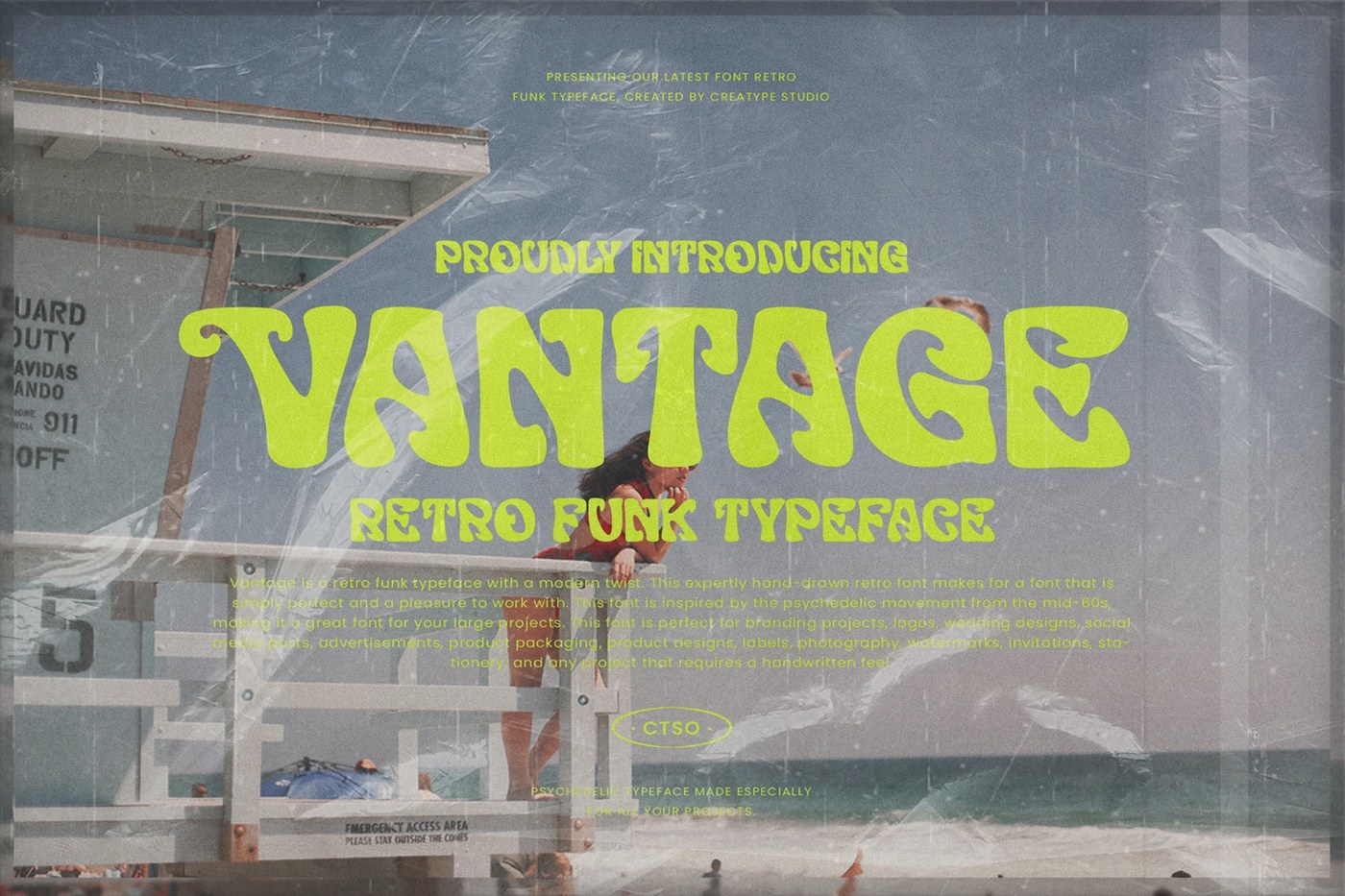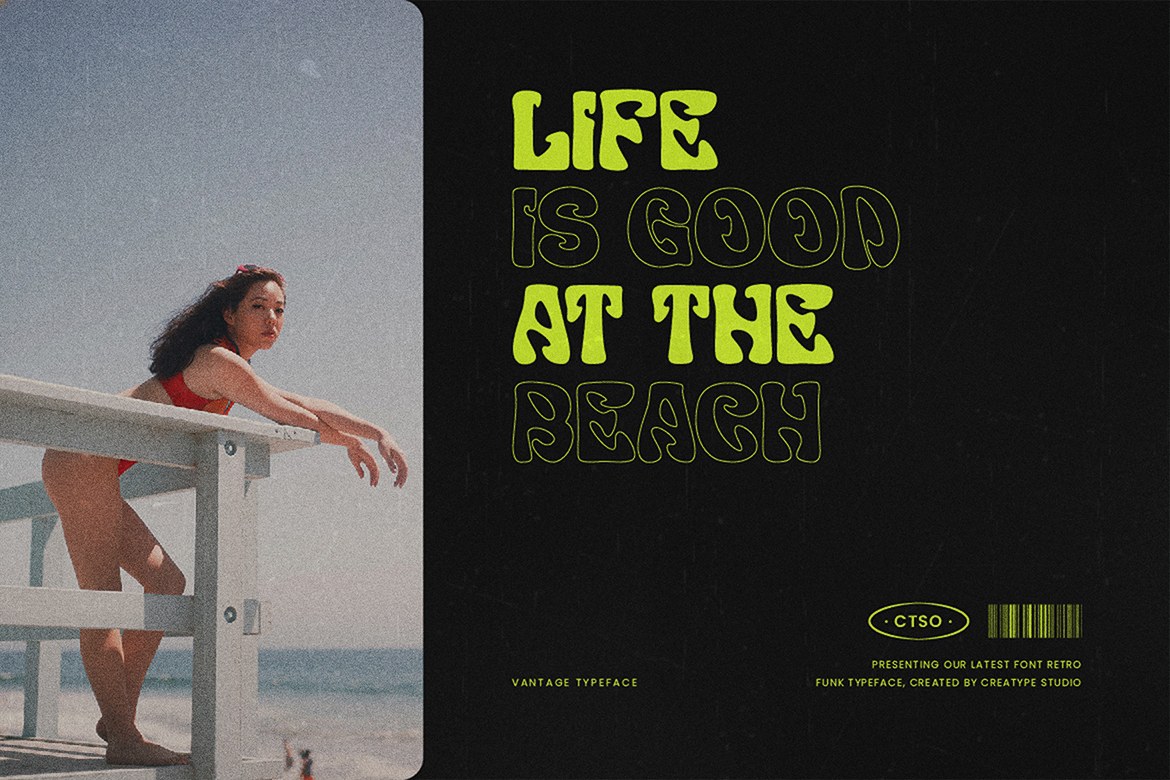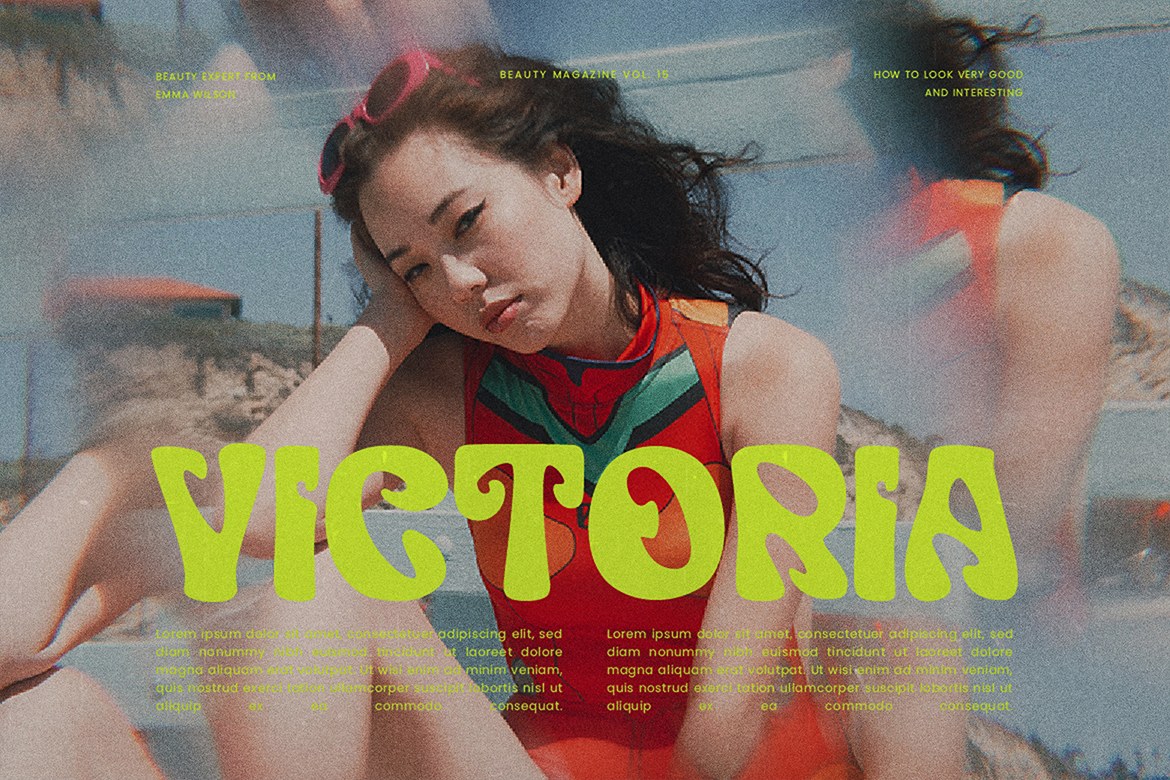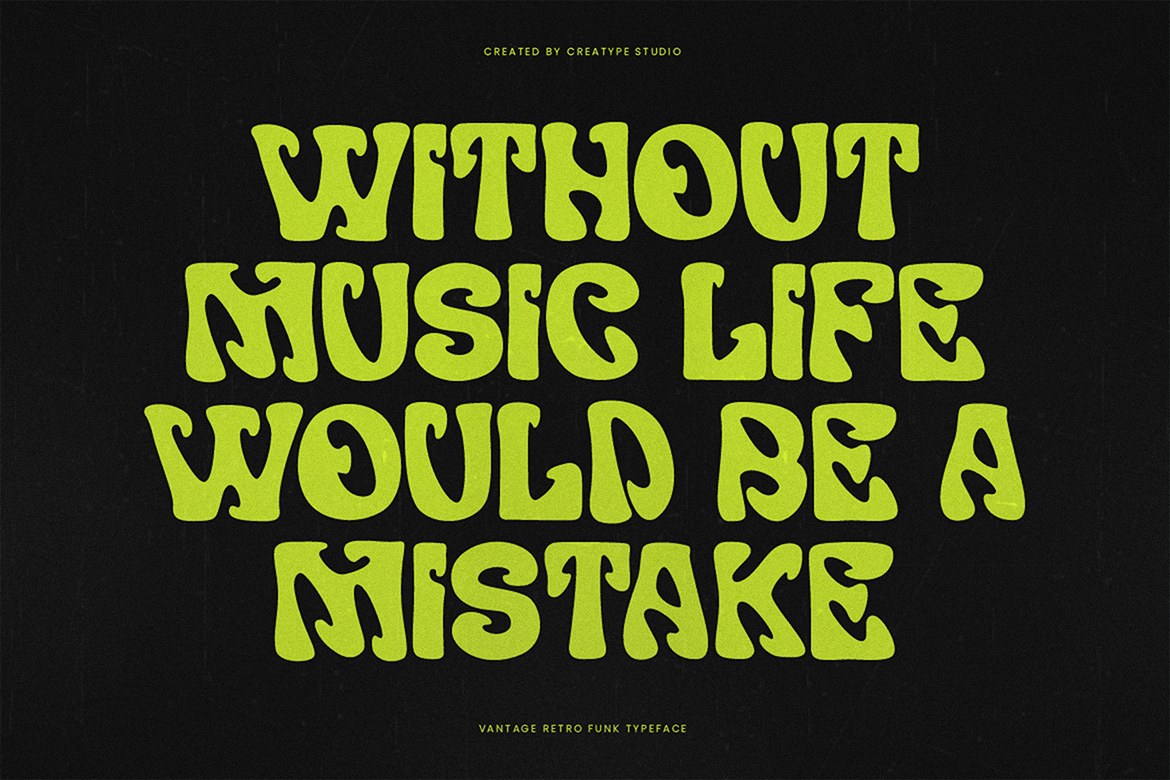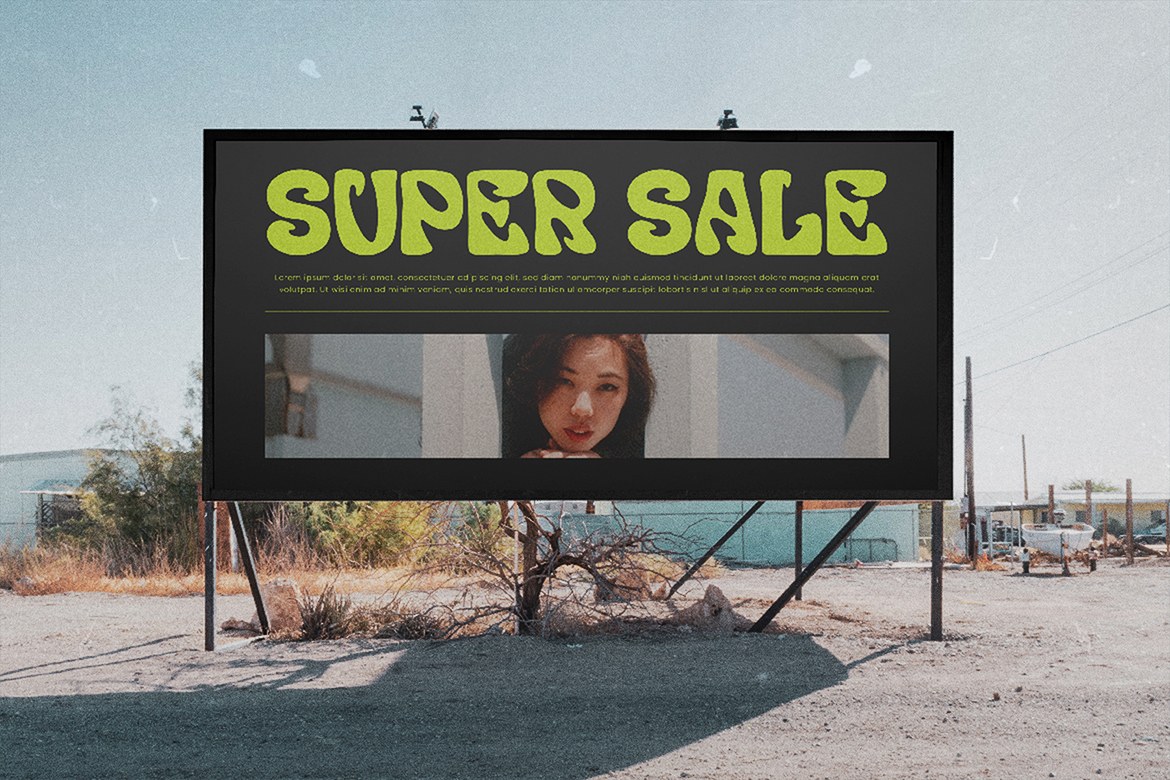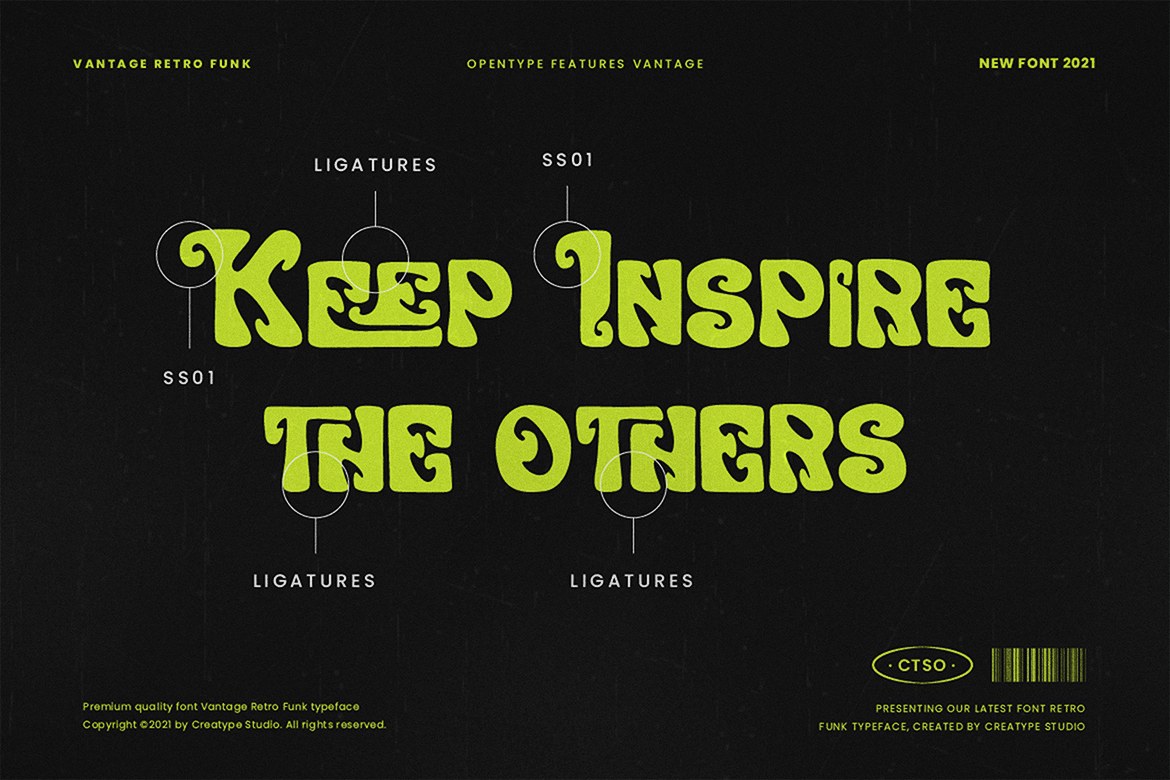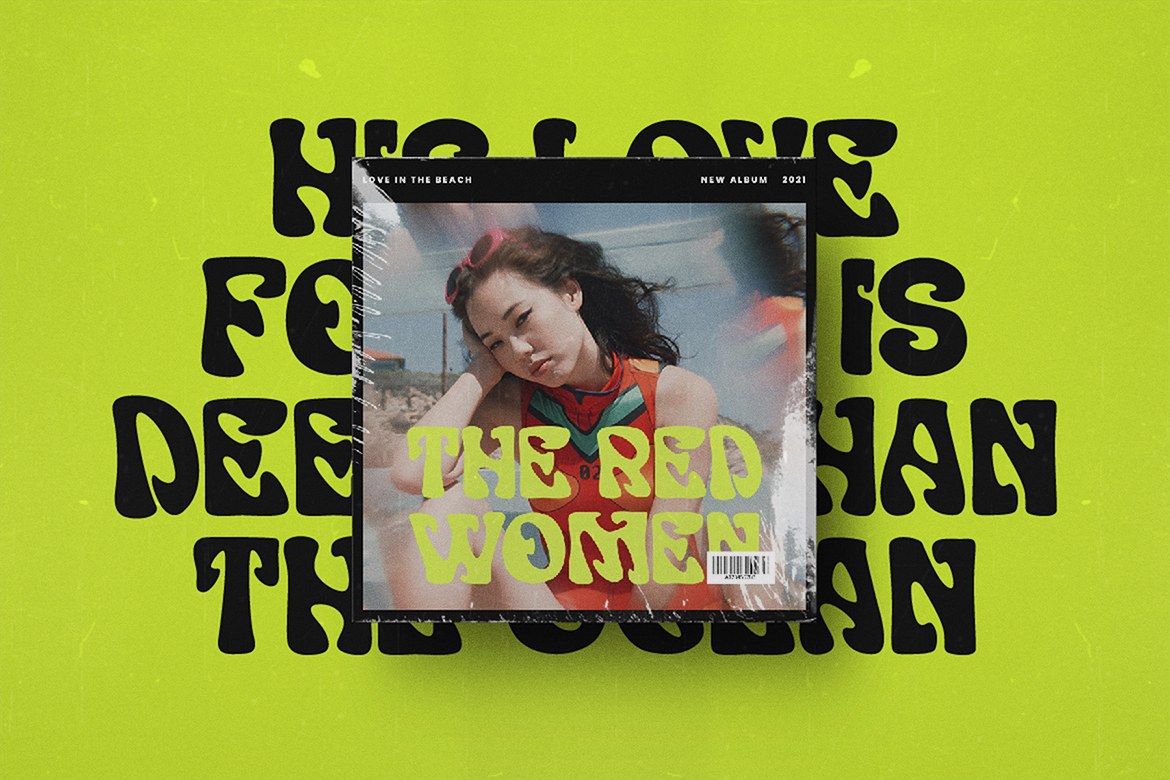
Vantage là bộ font chữ hiển thị (display font) được thiết kế theo phong cách vẽ tay, mang đậm hơi thở Retro và Psychedelic, cực kỳ phù hợp cho các dự án branding hiện đại.
Bộ font này tái hiện lại tinh thần sáng tạo của phong trào phản văn hóa (counterculture) giữa những năm 60. Các chi tiết vẽ tay tỉ mỉ mang đến kết cấu tự nhiên cho từng ký tự. Với đường nét uyển chuyển, Vantage tạo ra một dòng chảy thị giác đẹp mắt khi sử dụng cho các tiêu đề poster lớn. Những nét vẽ đậm tạo cảm giác chắc chắn, vững chãi, giúp bố cục trang giấy có một sức hút mạnh mẽ. Khoảng trống âm (negative space) xung quanh các con chữ cũng được tính toán kỹ để đảm bảo khả năng đọc tốt khi in ấn. Việc sắp xếp khoảng cách chữ (letter-spacing) chặt chẽ giúp các từ kết nối với nhau thành một khối thị giác đồng nhất. Từng đường cong đều gợi nhớ đến phong cách trên các bìa đĩa than và poster âm nhạc cổ điển.
Vantage được xây dựng dựa trên một hệ thống typography kỷ luật, có khả năng mở rộng linh hoạt từ các nền tảng vật lý đến kỹ thuật số. Cấu trúc lưới Thụy Sĩ (Swiss grid) ẩn bên dưới giúp các chữ cái đạt được sự hài hòa về hình học. Các font chữ có độ tương phản cao này khi kết hợp với những khối văn bản sans-serif sạch sẽ sẽ tạo nên hiệu ứng thẩm mỹ tuyệt vời. Trong lĩnh vực in ấn, việc sử dụng giấy không tráng phủ (uncoated paper) với độ thấm mực sâu sẽ càng làm tôn lên vẻ đẹp hoài cổ của font chữ.
Đây là một tài nguyên thiết kế giá trị từ Creatype Studio Gallery, vừa tôn vinh lịch sử thiết kế vừa đáp ứng tốt các nhu cầu công năng hiện đại. Vantage giúp các designer tạo ra những bộ nhận diện hình ảnh nổi bật, đặc biệt là trong lĩnh vực thiết kế bao bì và Merchandise. Phong cách Vintage Funk này vẫn giữ nguyên được giá trị và sự khác biệt so với những font chữ trung tính thông thường.